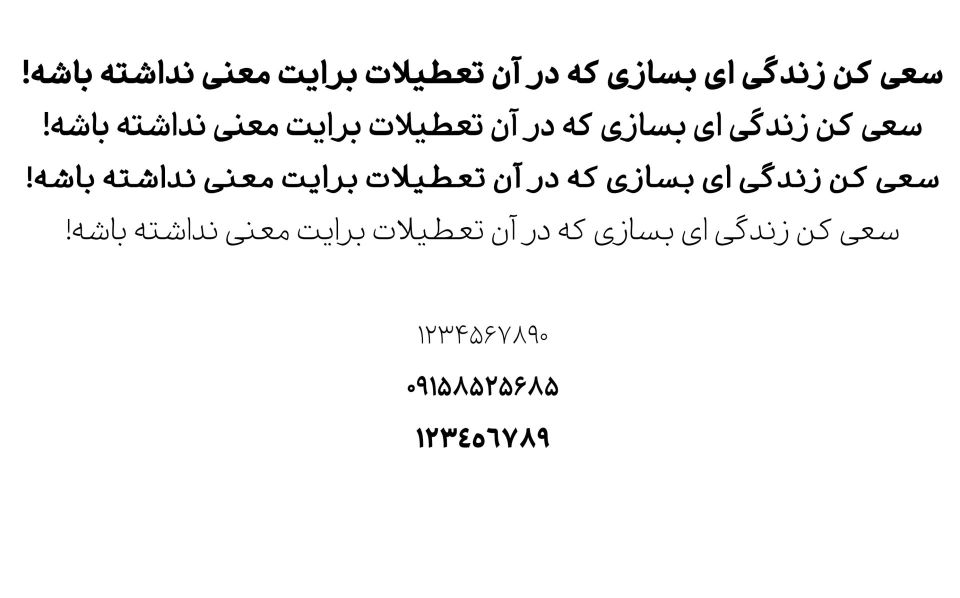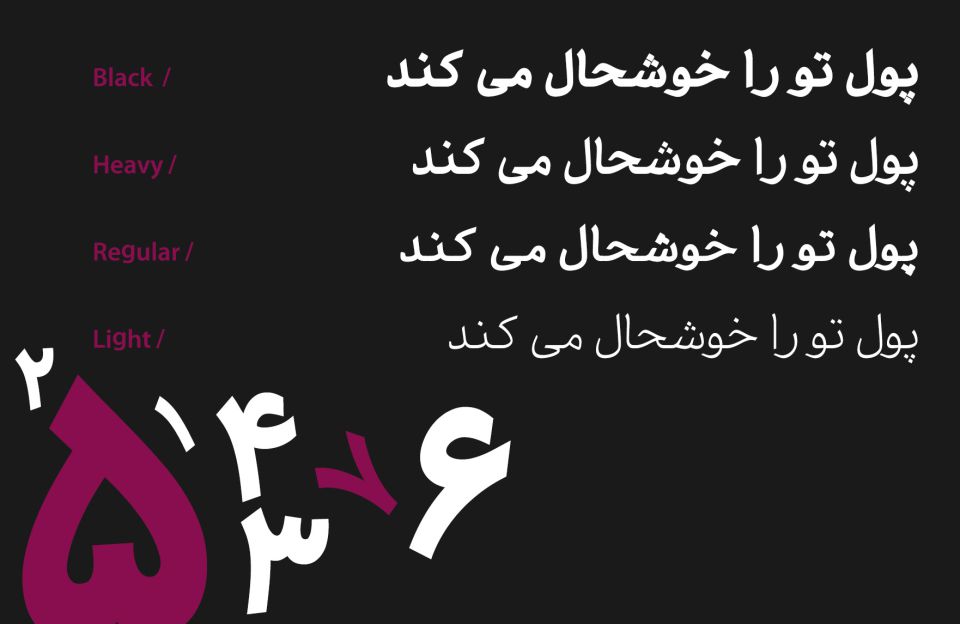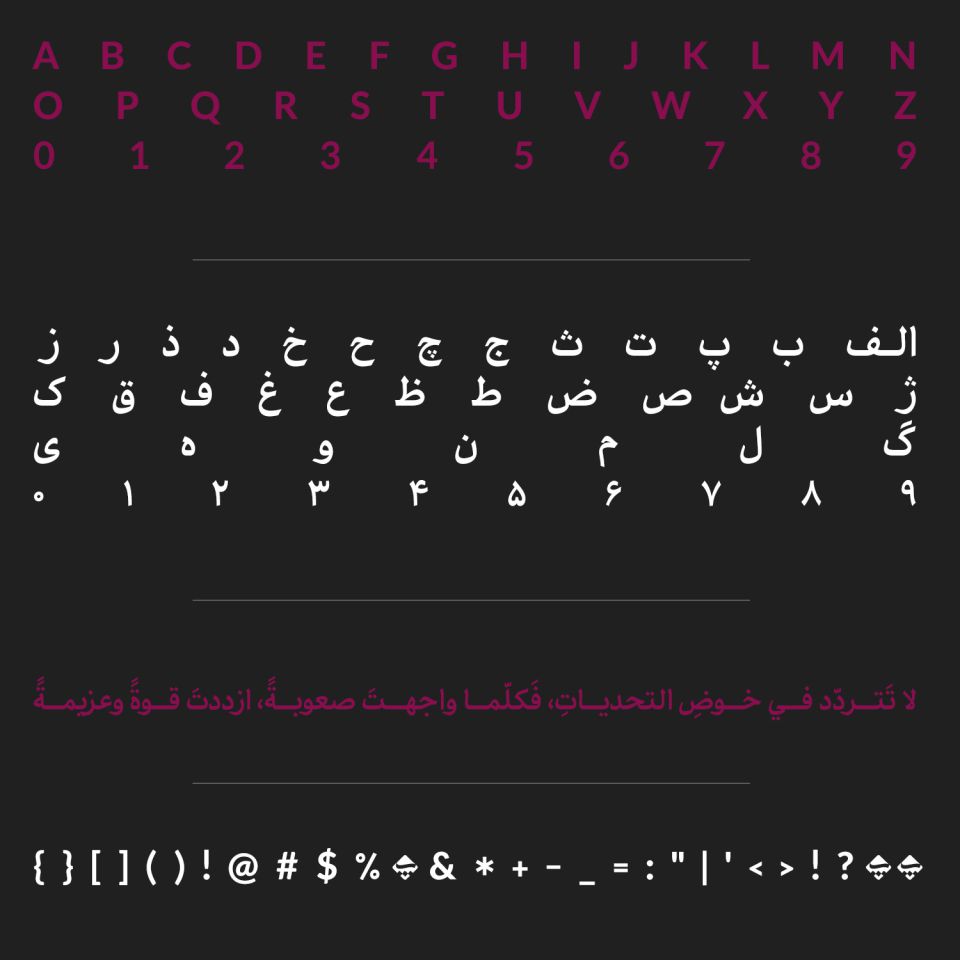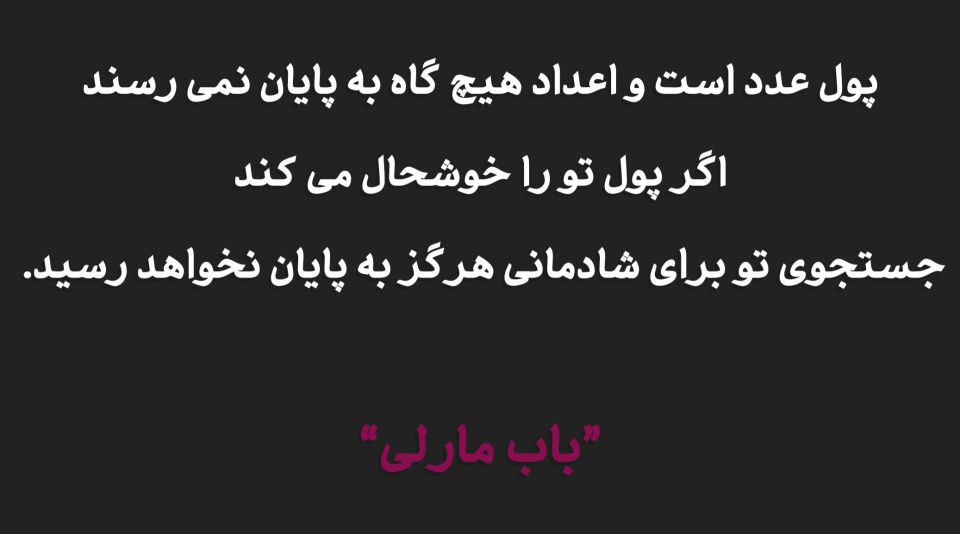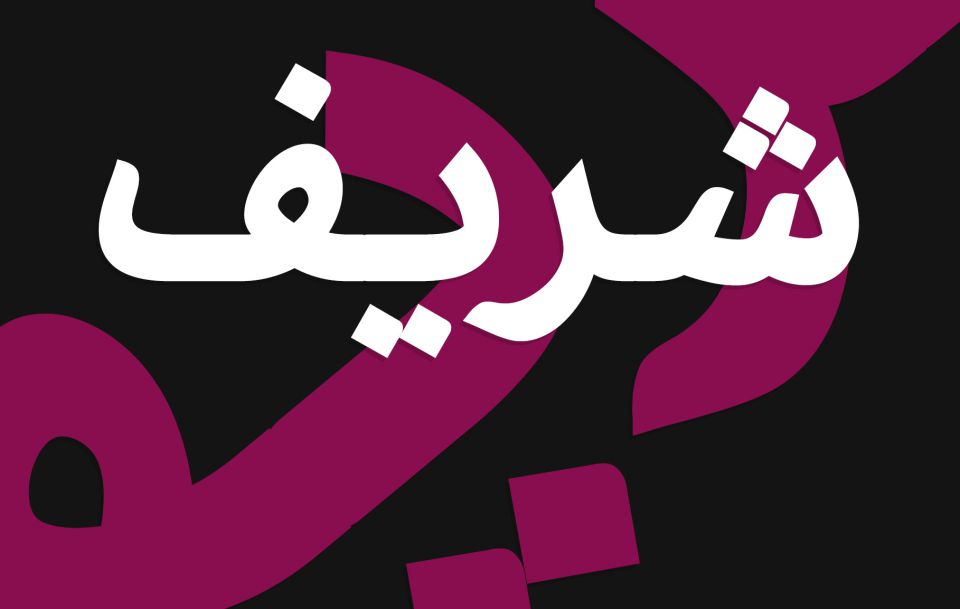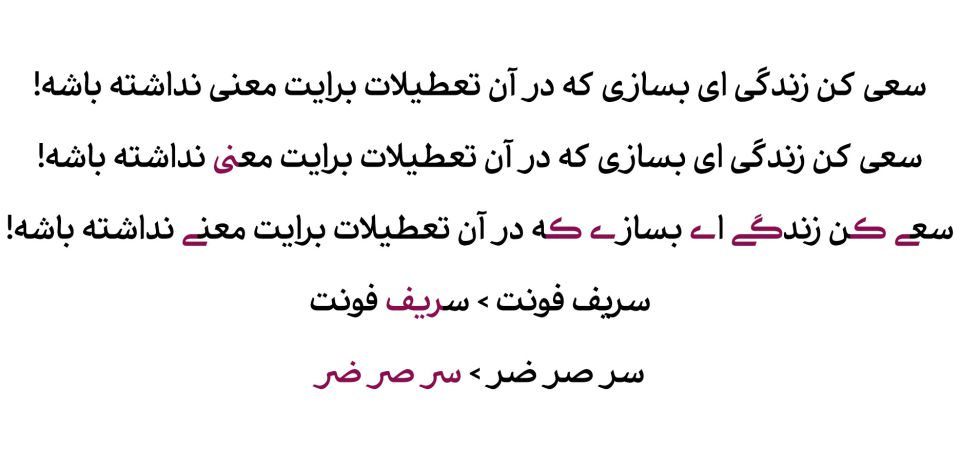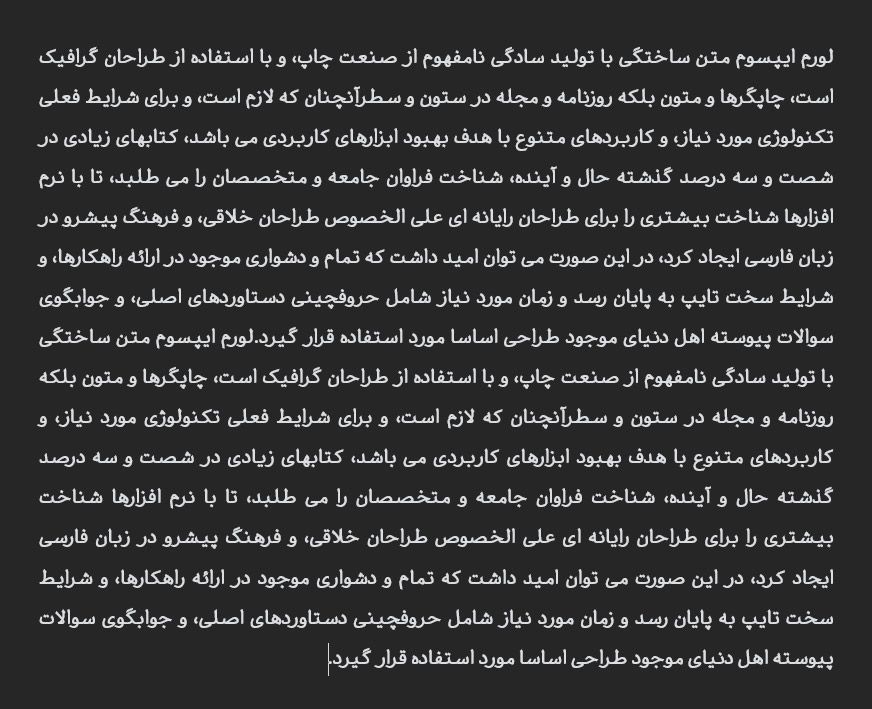
4 فونت ویژه فارسی
| ⭐ توضیحات | نسخه شبیه سازی شده فونت ویژه پشتیبانی از حروف فارسی و انگلیسی اعداد فارسی Fu Num و انگلیسی EN Num بهمراه نسخه وب دارای حروف جایگزینزیبایی و ظرافت را به پروژههای طراحی خود هدیه دهید. فونت ویژه را دانلود کنید و از خوانایی و زیبایی آن در طراحیهای خود لذت ببرید. 4 وزن مختلف |
دانلود فونت ویژه ارتقای زیبایی به پروژههای طراحی شما
فونتهای زیبا و خوانا نقش بسزایی در انتقال پیام و جلب توجه مخاطب در پروژههای طراحی گرافیک، وبسایتها و محتواهای دیجیتال ایفا میکنند. در این میان، فونتهای فارسی حرفهای که متناسب با نیازهای روز طراحی شدهاند، اهمیت ویژهای دارند. فونت ویژه یکی از این فونتهای خاص و خوشنویسیشده است که میتواند جلوهای ویژه به آثار شما ببخشد.
آشنایی با فونت ویژه ظرافت در عین سادگی
فونت ویژه یک فونت فارسی بدون-سریف (Sans-Serif) است که با الهام از خط نستعلیق طراحی شده است. این فونت با حفظ سادگی و خوانایی، حس ظرافت و زیبایی خاصی را به همراه دارد. حروف Vije با ضخامت یکنواخت و گوشههای نرم طراحی شدهاند که برای استفاده در عناوین، متنهای بدنه و حتی طراحی لوگو مناسب است.
ویژگیهای برجسته فونت ویژه
علاوه بر زیبایی بصری، فونت ویژه از ویژگیهای فنی قابل توجهی نیز برخوردار است:
- خوانایی بالا: طراحی حرفهای فونت ویژه باعث میشود که خواندن متون نوشتهشده با این فونت، در اندازههای مختلف، آسان باشد. این ویژگی، Vije را به گزینهای ایدهآل برای وبسایتها و محتواهای دیجیتال تبدیل میکند.
- پشتیبانی از حروفگذاری متنوع: فونت ویژه از تمامی حروف و علائم زبان فارسی، به همراه حروف لاتین و اعداد، پشتیبانی میکند. این ویژگی باعث میشود که بتوانید از این فونت برای نوشتن انواع متون و محتوا استفاده کنید.
- وزنهای متنوع: طراحان فونت ویژه، وزنهای مختلفی از جمله (Light، Regular، Heavy) را برای این فونت در نظر گرفتهاند. این وزنهای متنوع به شما امکان میدهند تا بر اساس نیاز خود، ضخامت فونت را تنظیم کرده و از آن در بخشهای مختلف پروژههای طراحی خود استفاده کنید.
دانلودکاربردهای فونت ویژه: درخشش در پروژههای مختلف
با توجه به ویژگیهای ذکر شده، فونت ویژه را میتوان در طیف وسیعی از پروژههای گرافیکی و دیجیتال به کار گرفت. برخی از کاربردهای اصلی این فونت عبارتند از:
- طراحی وبسایت: فونت ویژه با خوانایی بالا و ظرافت بصری، انتخابی عالی برای طراحی رابط کاربری (UI) و متنهای بدنه وبسایتها است.
- طراحی اپلیکیشن: این فونت برای طراحی رابط کاربری اپلیکیشنهای موبایل و تبلت نیز مناسب است و میتواند تجربه کاربری لذتبخشی را برای مخاطبان به همراه داشته باشد.
- طراحی گرافیک: طراحان گرافیک میتوانند از فونت ویژه در طراحی بروشورها، پوسترها، کارتهای ویزیت، بنرهای تبلیغاتی و سایر عناصر گرافیکی استفاده کنند.
- طراحی محتوا: به کار بردن فونت ویژه در طراحی اینفوگرافیکها، اسلایدهای ارائه و دیگر محتواهای دیجیتال میتواند جلوهای حرفهای و جذاب به آنها ببخشد.
- طراحی لوگو: وزنهای Heavy و Black فونت ویژه برای طراحی لوگوهایی با سبک مینیمالیستی و مدرن مناسب است.
4. چه تفاوتی بین فونت ویژه و سایر فونتهای فارسی وجود دارد؟
فونت ویژه با ظرافت و زیبایی منحصر به فرد خود، از بسیاری از فونتهای فارسی دیگر متمایز میشود. این فونت با الهام از خط نستعلیق طراحی شده و حروف آن ضخامت یکنواخت و گوشههای نرم دارند.